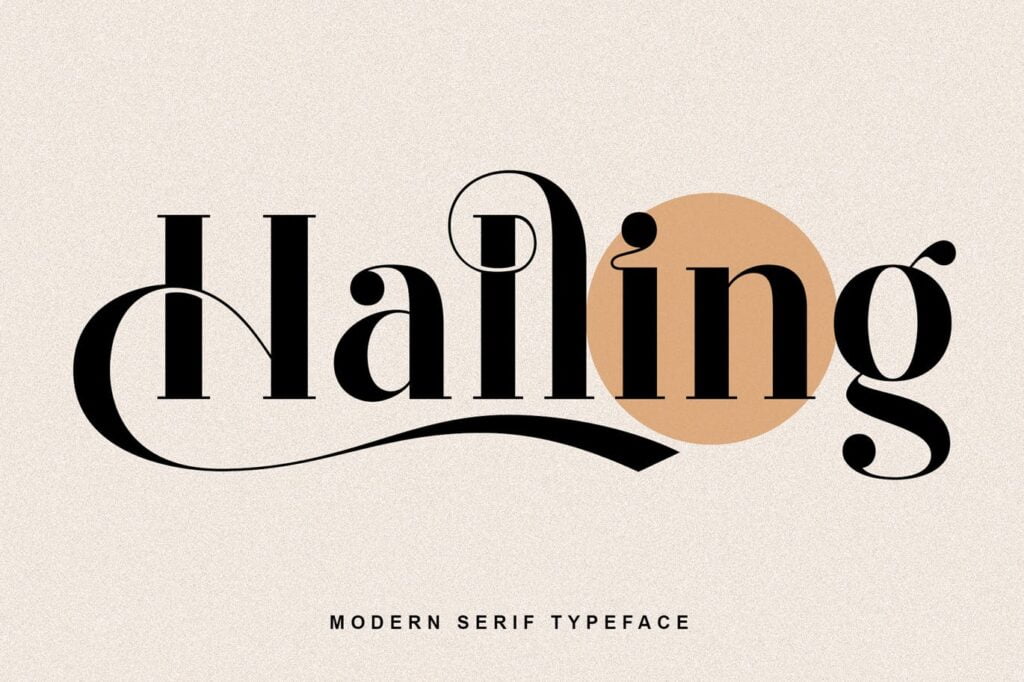
Halling Font
Bonjour, cette fois, nous souhaitons vous presenter un nouveau produit, a savoir « Halling Typeface », une police d’affichage Serif au style classique, feminin et elegant.
Halling Modern Serif Font